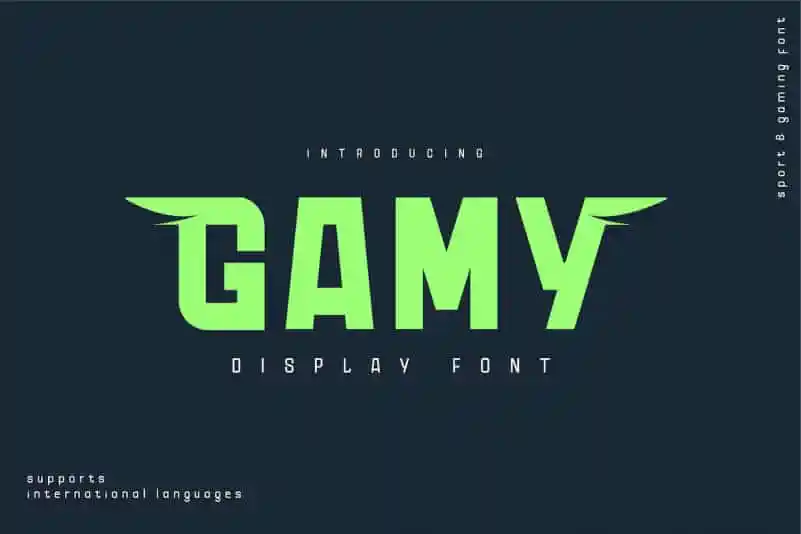
Gamy Sans Serif Font – Download Grátis
A Gamy Sans Serif é uma fonte serifa clara que foi pensada para se encaixar perfeitamente nos diferentes meios de design. Composta com precisão e proporção, ela é ideal para adicionar um toque moderno aos seus projetos. O destaque em cada alternativa de letra maiúscula dá ao conjunto uma ar robusta e forte, criando um impacto visual notável. Esta fonte perfeita para designers que buscam uma sensação atrevida e moderna, combinada com a elegância das letras sem serifas, torna-a uma opção ideal tanto para projetos visuais como de texto. Ideal para destacar o design em sua próxima peça de trabalho, a Gamy Sans Serif é uma escolha segura para qualquer designer que deseja adicionar um toque único e moderno ao seu projeto.